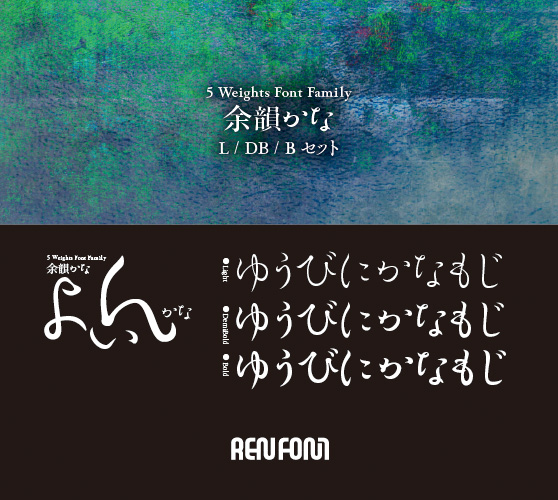
行書体
余韻かな-中・小見出し用3ウェイトセット(L/DB/B)
味わい深い余韻を残す印象的な書体。究極の流麗さを追求した、明朝風と行書風のハイブリッドフォルムフォントです。
特徴が強いので、長文には向きませんが、短い本文組みや、ちょっとした見出しに使ってみてください。躍動感に満ちた、訴求力のある紙面になるはずです。縦組み、横組みともプロポーショナル加工を加えました。また、ペアカーニングも緻密にほどこしてあります。中・小見出し用3ウェイトセット。